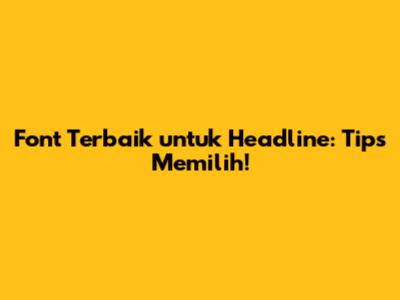
Font Terbaik Untuk Headline: Tips Memilih!
Memilih font yang cocok untuk headline adalah langkah krusial dalam desain visual. Headline adalah wajah dari sebuah konten, baik itu artikel blog, iklan, poster, atau materi pemasaran lainnya. Pemilihan font yang tepat dapat menarik perhatian pembaca, menyampaikan pesan dengan efektif, dan memperkuat identitas merek. Sebaliknya, font yang buruk dapat membuat headline terlihat tidak menarik, sulit dibaca, atau bahkan merusak citra merek. Dalam artikel ini, kita akan membahas berbagai faktor yang perlu dipertimbangkan saat memilih font untuk headline, memberikan rekomendasi font populer, dan memberikan tips praktis untuk memastikan headline Anda tampil menonjol dan efektif.
Mengapa Pemilihan Font Headline Sangat Penting?
Headline adalah elemen pertama yang dilihat oleh audiens. Headline yang menarik dan mudah dibaca akan membuat audiens tertarik untuk membaca lebih lanjut. Mari kita bahas mengapa pemilihan font yang tepat untuk headline itu sangat esensial:
1. Menarik Perhatian: Headline yang menggunakan font yang unik dan menarik dapat langsung memikat perhatian pembaca. Font yang berbeda dapat memberikan kesan visual yang kuat dan membuat headline lebih menonjol di antara konten lainnya. Misalnya, penggunaan font tebal dan besar dengan desain yang unik dapat membuat headline terlihat lebih mencolok.
2. Menyampaikan Pesan: Font memiliki karakter dan kepribadiannya sendiri. Pemilihan font yang sesuai dengan pesan yang ingin disampaikan dapat membantu memperkuat makna headline. Misalnya, font serif klasik seperti Times New Roman atau Garamond dapat memberikan kesan formal dan profesional, sementara font sans-serif modern seperti Helvetica atau Arial dapat memberikan kesan bersih dan minimalis.
3. Membangun Identitas Merek: Konsistensi dalam penggunaan font headline dapat membantu membangun identitas merek yang kuat dan mudah dikenali. Dengan menggunakan font yang sama untuk headline di semua materi pemasaran, merek Anda akan terlihat lebih profesional dan terpercaya. Misalnya, Coca-Cola menggunakan font script yang khas untuk logonya dan headline iklannya, yang membantu membangun identitas merek yang ikonik.
4. Meningkatkan Keterbacaan: Headline yang mudah dibaca akan membuat pembaca lebih nyaman dan tertarik untuk membaca lebih lanjut. Pemilihan font yang jelas dan memiliki ukuran yang cukup besar akan memastikan bahwa headline dapat dibaca dengan mudah, bahkan dari jarak jauh atau pada layar kecil. Hindari penggunaan font yang terlalu rumit atau memiliki dekorasi yang berlebihan, karena dapat mengganggu keterbacaan.
5. Menciptakan Hierarki Visual: Penggunaan font yang berbeda untuk headline, subheadline, dan body text dapat membantu menciptakan hierarki visual yang jelas. Headline harus menggunakan font yang paling menonjol untuk menarik perhatian utama, sementara subheadline dan body text dapat menggunakan font yang lebih sederhana untuk memberikan informasi tambahan. Hierarki visual yang baik akan membantu pembaca memahami struktur konten dengan lebih mudah.
Faktor-Faktor yang Perlu Dipertimbangkan Saat Memilih Font untuk Headline
Sebelum memutuskan font yang paling cocok untuk headline Anda, ada beberapa faktor penting yang perlu dipertimbangkan:
1. Kesesuaian dengan Topik dan Gaya: Pertimbangkan topik dan gaya konten Anda. Apakah konten Anda serius dan formal, atau santai dan informal? Pilih font yang mencerminkan suasana dan pesan yang ingin disampaikan. Misalnya, jika Anda menulis tentang keuangan, font serif klasik mungkin lebih cocok, sementara jika Anda menulis tentang teknologi, font sans-serif modern mungkin lebih sesuai.
2. Keterbacaan: Pastikan font yang Anda pilih mudah dibaca dalam berbagai ukuran dan format. Uji coba font pada berbagai perangkat dan resolusi layar untuk memastikan keterbacaannya tetap optimal. Hindari penggunaan font yang terlalu tipis atau terlalu tebal, karena dapat mengganggu keterbacaan.
3. Kontras: Pastikan ada kontras yang cukup antara font headline dan latar belakangnya. Headline harus terlihat jelas dan mudah dibaca, bahkan dalam kondisi pencahayaan yang kurang baik. Gunakan warna yang kontras untuk membuat headline lebih menonjol. Misalnya, headline hitam pada latar belakang putih atau headline putih pada latar belakang gelap.
4. Ukuran Font: Pilih ukuran font yang sesuai dengan ukuran headline dan tata letak keseluruhan. Headline harus cukup besar untuk menarik perhatian, tetapi tidak terlalu besar sehingga terlihat berlebihan. Sesuaikan ukuran font dengan jenis perangkat yang digunakan oleh audiens Anda. Misalnya, headline pada perangkat seluler mungkin perlu lebih besar daripada headline pada desktop.
5. Jumlah Karakter: Pertimbangkan jumlah karakter dalam headline Anda. Headline yang terlalu panjang dapat terlihat padat dan sulit dibaca. Usahakan untuk membuat headline yang singkat, padat, dan mudah diingat. Gunakan kata-kata kunci yang relevan untuk menarik perhatian pembaca.
6. Lisensi Font: Pastikan Anda memiliki lisensi yang sah untuk menggunakan font yang Anda pilih, terutama jika Anda menggunakannya untuk tujuan komersial. Banyak font gratis yang tersedia, tetapi pastikan untuk memeriksa persyaratan lisensinya sebelum menggunakannya. Beberapa font mungkin hanya boleh digunakan untuk tujuan pribadi, sementara yang lain mungkin memerlukan pembayaran untuk penggunaan komersial.
Rekomendasi Font Populer untuk Headline
Berikut adalah beberapa rekomendasi font populer yang cocok untuk headline:
1. Serif:
• Times New Roman: Klasik dan formal, cocok untuk konten serius dan profesional.
• Garamond: Elegan dan mudah dibaca, cocok untuk konten yang menekankan keindahan dan keanggunan.
• Merriweather: Modern dan serbaguna, cocok untuk berbagai jenis konten.
• Playfair Display: Cocok untuk headline yang membutuhkan sentuhan klasik namun tetap modern.
2. Sans-Serif:
• Helvetica: Bersih dan minimalis, cocok untuk konten modern dan teknologi.
• Arial: Serbaguna dan mudah dibaca, cocok untuk berbagai jenis konten.
• Roboto: Modern dan ramah, cocok untuk konten digital.
• Open Sans: Sangat mudah dibaca di berbagai ukuran layar.
3. Display Fonts:
• Bebas Neue: Tebal dan modern, cocok untuk headline yang ingin menonjol.
• Oswald: Kuat dan dinamis, cocok untuk headline yang ingin menyampaikan energi dan semangat.
• Montserrat: Geometris dan modern, memberikan kesan futuristik.
• Raleway: Elegan dan tipis, cocok untuk desain yang lebih halus.
4. Script Fonts:
• Pacifico: Santai dan ramah, cocok untuk konten yang ingin terlihat lebih personal.
• Lobster: Klasik dan elegan, cocok untuk headline yang ingin memberikan kesan mewah.
Tips Praktis Memilih dan Menggunakan Font untuk Headline
Selain mempertimbangkan faktor-faktor di atas, berikut adalah beberapa tips praktis untuk memilih dan menggunakan font yang ideal untuk headline:
1. Gunakan Kombinasi Font yang Tepat: Kombinasikan font headline dengan font body text yang berbeda untuk menciptakan kontras dan hierarki visual yang jelas. Hindari menggunakan terlalu banyak font yang berbeda dalam satu desain, karena dapat terlihat berantakan dan tidak profesional. Pilih dua atau tiga font yang saling melengkapi dan gunakan secara konsisten.
2. Perhatikan Spasi: Atur spasi antara huruf dan kata dengan hati-hati untuk memastikan keterbacaan yang optimal. Spasi yang terlalu sempit dapat membuat headline terlihat padat dan sulit dibaca, sementara spasi yang terlalu lebar dapat membuat headline terlihat terpisah-pisah. Gunakan alat bantu desain untuk mengatur spasi dengan presisi.
3. Eksperimen dengan Warna: Gunakan warna untuk membuat headline lebih menonjol dan menarik perhatian. Pilih warna yang sesuai dengan identitas merek Anda dan pesan yang ingin Anda sampaikan. Gunakan warna yang kontras dengan latar belakang untuk memastikan keterbacaan yang optimal. Hindari penggunaan terlalu banyak warna yang berbeda dalam satu headline, karena dapat terlihat berlebihan.
4. Uji Coba pada Berbagai Perangkat: Uji coba headline Anda pada berbagai perangkat dan resolusi layar untuk memastikan keterbacaannya tetap optimal. Perangkat seluler mungkin memerlukan ukuran font yang lebih besar daripada desktop. Pastikan headline Anda terlihat bagus di semua perangkat yang digunakan oleh audiens Anda.
5. Minta Pendapat: Minta pendapat dari teman, kolega, atau desainer profesional untuk mendapatkan masukan yang berharga. Mereka mungkin memiliki perspektif yang berbeda dan dapat memberikan saran yang membantu Anda memilih font yang paling efektif untuk headline Anda.
Kesimpulan
Memilih font yang tepat untuk headline adalah investasi penting dalam desain visual Anda. Dengan mempertimbangkan faktor-faktor seperti kesesuaian dengan topik, keterbacaan, kontras, dan ukuran font, Anda dapat menciptakan headline yang menarik perhatian, menyampaikan pesan dengan efektif, dan memperkuat identitas merek Anda. Jangan ragu untuk bereksperimen dengan berbagai font dan kombinasi warna untuk menemukan yang paling sesuai dengan kebutuhan Anda. Dengan pemilihan font yang tepat, headline Anda akan menjadi daya tarik utama yang memikat pembaca dan mendorong mereka untuk membaca lebih lanjut.
Jadi, guys, jangan anggap remeh pemilihan font untuk headline, ya! Ini adalah salah satu elemen penting yang bisa membuat konten kalian jadi lebih menarik dan profesional. Semoga artikel ini bermanfaat dan membantu kalian dalam memilih font yang paling tepat untuk headline kalian. Selamat mencoba dan semoga sukses!